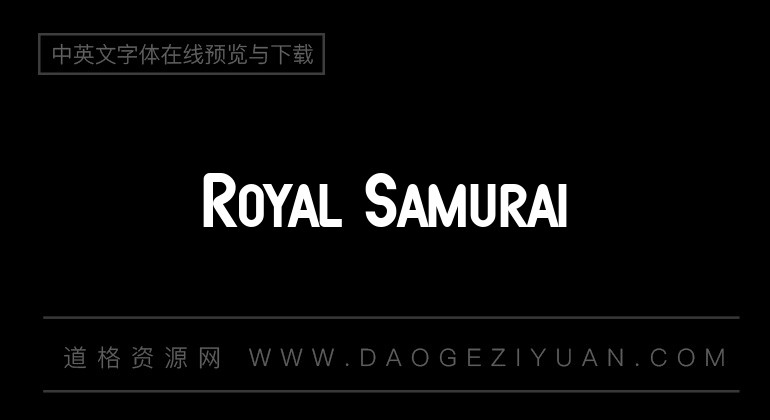
Royal Samurai是一款精致的日本风格字体,它受到日本武士的精神灵感而设计。它的字体分析特点为粗细错落的线条,有着浓厚的日本风情。它的字体特点是精致的笔画,极具视觉冲击力。Royal Samurai字体可以用于各种类型的印刷品,如海报、书籍、杂志、网页等,以及商业用途,如品牌标识、广告牌等。内容介绍
Royal Samurai是一款非常不错的手写艺术字体,具有很好的视觉感,适合于文化类的宣传设计、商业类品牌的广告和产品包装设计以及个性化文字排版等较多场景。